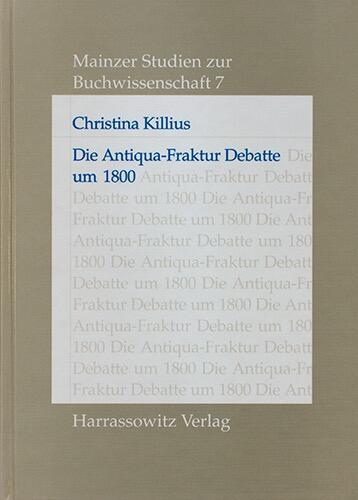
Der Antiqua-Fraktur-Streit spitze sich bekanntlich insbesondere gegen Ende des 19. und Anfang des 20. Jahrhunderts zu. Er schwelte aber über mehrere Jahrhunderte und flammte auch zur Zeit der Weimarer Klassik schon einmal kräftig auf. Über diese Phase des Antiqua-Fraktur-Streites berichtet dieses Buch von Christina Killius.
Im Mittelpunkt des ersten Teils der Arbeit steht neben einem Abriss der Geschichte der beiden Schriftstile auch eine Analyse der geistesgeschichtlichen Hintergründe und der spezifischen Voraussetzungen für die Entwicklung der Antiqua und der gebrochenen Schrift. Darauf aufbauend werden im Anschluss die Gründe der allgemeine Verbreitung der gebrochenen Schrift im deutschsprachigen Raum seit dem 17. Jahrhundert untersucht. Es folgen die Betrachtungen zur Lage gegen Ende des 18. Jahrhunderts. Während etwa in England, Frankreich und Italien neue Akzente gesetzt werden, zeigt sich das deutsche Buchgewerbe eher rückständig. Einige Verleger und Autoren liebäugeln daher mit den gerade im Ausland entstehenden Formidealen des Klassizismus und es entstehen einzelne deutsche Druckwerke im klassizistischen Stil mit Antiqua-Lettern. Begleitet werden diese Werke von einem heftigen Fachstreit, der sich über Veröffentlichungen und Briefe nachvollziehen lässt. Mit vielen Zitaten und Beispielabbildungen aus dieser Zeit wird der Antiqua-Fraktur-Streit um 1800 in diesem fast 500 Seiten umfassenden Werk ausführlich kulturhistorisch beleuchtet. Ins 19. Jahrhundert erfolgt dann nur noch ein Ausblick. Hier bildet das Buch Fraktur oder Antiqua von Silvia Hartmann den perfekten Anschluss.